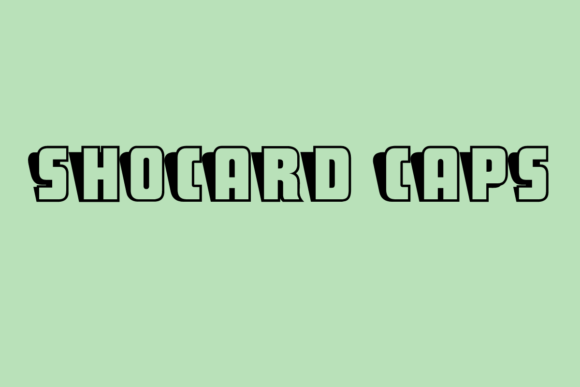
ShoCard Caps, fuente retro en negrita escrita a mano
ShoCard Caps es una fuente retro para display, diseñada con letras 3D impactantes y un aire de póster vintage. Sus contornos audaces y su aspecto sombreado evocan el diseño clásico de mediados del siglo XX, ideal para titulares, pósteres, branding y merchandising vintage. Ya sea que diseñes ropa, señalización, anuncios impresos o gráficos digitales, ShoCard Caps aporta carácter e impacto visual.
- Conjunto completo de glifos: letras mayúsculas, números, puntuación, caracteres especiales (según lo proporcionado por el diseñador de la fuente original)
ShoCard Caps ofrece un aire retro instantáneo y un gran impacto visual, ideal para proyectos que requieren titulares llamativos o un estilo vintage. Sus letras 3D/sombreadas resaltan en ropa, pósteres y merchandising, lo que las hace ideales para diseños que buscan llamar la atención. Al ser una fuente gratuita con licencia de uso comercial (tal como se ofrece en su fuente original), es una forma asequible de añadir tipografía distintiva a tus diseños, ideal tanto para pequeñas empresas, vendedores bajo demanda como para estudios creativos.
| Característica | Tapas ShoCard | Fuente de visualización moderna genérica A | Fuente genérica de contorno retro B |
| Estilo / Vibra | Pantalla retro audaz, 3D/sombreada, inspirada en pósteres vintage | Pantalla moderna y limpia, minimalista. | Contorno de estilo retro pero plano, menos profundidad. |
| Mejor caso de uso | Carteles vintage, merchandising, branding, titulares llamativos, productos de temática retro | Logotipos modernos, etiquetas de productos limpias, marca minimalista. | Titulares de temática retro o impresiones decorativas, pero de menor impacto que las fuentes 3D/sombreadas |